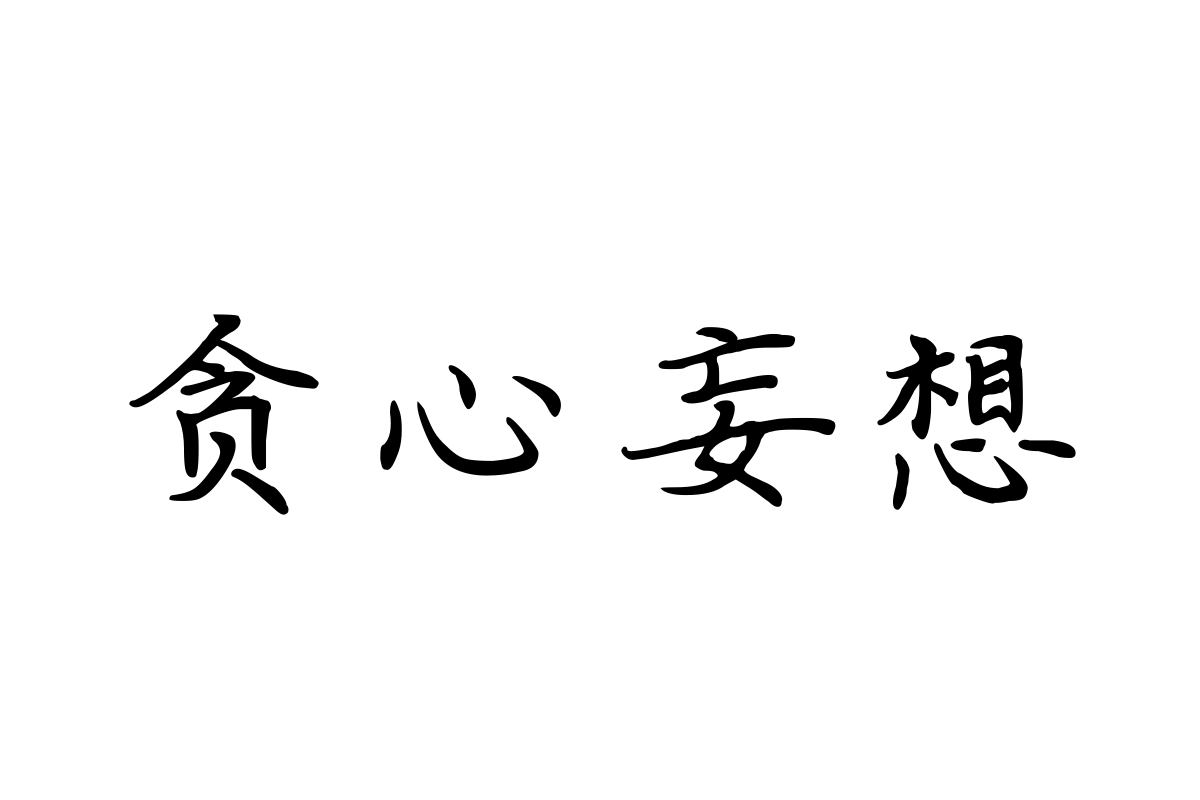
三极枝洁楷书是一种具有独特风格的汉字书写字体,它源自日本。这种字体的特点是笔画清晰、结构严谨,给人一种简洁明了的感觉。
在设计上,三极枝洁楷书采用了传统的楷书结构,但在笔画的处理上进行了一些创新。例如,它的横画和竖画都采用了直线的形式,使得整个字形更加规整。此外,它还在一些笔画的连接处增加了一些细微的变化,使得整个字体更加生动有趣。
总的来说,三极枝洁楷书是一种非常适合用于书法和印刷的字体,它的简洁明了和独特风格使它受到了很多书法家和设计师的喜爱。